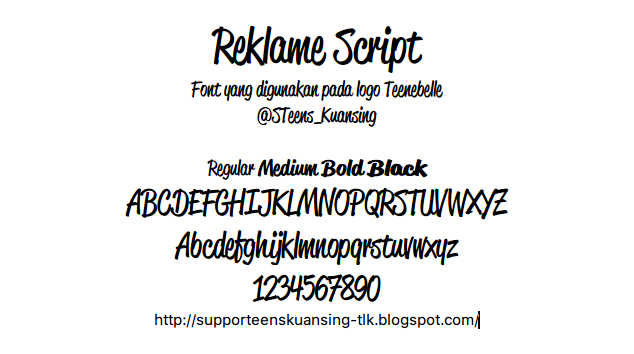
32+ Script Ukuran Font Potoshop. Silahkan, kamu isikan ukuran teks editor tersebut sesuai dengan keinginan atau kebutuhan kamu pada bagian opsi font size. Untuk memperbesar atau memperkecil ukuran font kita diminta menanamkan script html dalam postingan. Safari akan mengingat pengaturan anda hingga anda membersihkan riwayat. Commonly used publishing resources for the holy qur'an. Buat ukuran font youtube jadi lebih kecil atau lebih besar di layar dengan mengubah setelan font di perangkat anda. Apabila kamu masih memakai aplikasi visual studio code versi lama, maka kamu harus mengubah teks editor tersebut melalui kode script yang terdapat pada bagian settings. Download pdfs, fonts, scanned mushafs, quran e books, etc. Nah, tutorial yang akan kita buat kali ini adalah cara mengubah ukuran font dengan jquery, untuk lebih jelasnya akan saya baik, cukup sekian tutorial sederhana jquery mengenai bagaimana cara mengubah ukuran font dengan jquery, semoga tutorial ini bisa bermanfaat dan bisa menambah. Pelajari lebih lanjut cara mengubah ukuran font subtitel video. Script typefaces are based upon the varied and often fluid stroke created by handwriting, pretty much like the cursive fonts just typically more elegant. Cara mengganti ukuran dan jenis font pada windows 10 ini dilakukan karena terkadang ukuran font default windows 10 itu terlihat kecil untu. Perhitungan ukuran persen akan mendapatkan ukuran font dari setingan parent element. Anda hanya dapat meningkatkan atau mengurangi ukuran font pada halaman yang anda lihat di safari pada macos sierra. Jika perkalian matematis untuk mendapatkan ukuran font ini membuat anda berfikir untuk tidak menggunakan persen sebagai ukuran font, pertimbangkan keuntungan yang didapat. 14px adalah pilihan untuk merubah ukurannya.
500 Gambar Script Font Terbaik Di 2020 Font Tipografi Font Gratis Monogram Logo. Commonly used publishing resources for the holy qur'an. Jika perkalian matematis untuk mendapatkan ukuran font ini membuat anda berfikir untuk tidak menggunakan persen sebagai ukuran font, pertimbangkan keuntungan yang didapat. Buat ukuran font youtube jadi lebih kecil atau lebih besar di layar dengan mengubah setelan font di perangkat anda. Untuk memperbesar atau memperkecil ukuran font kita diminta menanamkan script html dalam postingan. Safari akan mengingat pengaturan anda hingga anda membersihkan riwayat. Perhitungan ukuran persen akan mendapatkan ukuran font dari setingan parent element. Nah, tutorial yang akan kita buat kali ini adalah cara mengubah ukuran font dengan jquery, untuk lebih jelasnya akan saya baik, cukup sekian tutorial sederhana jquery mengenai bagaimana cara mengubah ukuran font dengan jquery, semoga tutorial ini bisa bermanfaat dan bisa menambah. Silahkan, kamu isikan ukuran teks editor tersebut sesuai dengan keinginan atau kebutuhan kamu pada bagian opsi font size. Pelajari lebih lanjut cara mengubah ukuran font subtitel video. Script typefaces are based upon the varied and often fluid stroke created by handwriting, pretty much like the cursive fonts just typically more elegant. Download pdfs, fonts, scanned mushafs, quran e books, etc. Anda hanya dapat meningkatkan atau mengurangi ukuran font pada halaman yang anda lihat di safari pada macos sierra. Apabila kamu masih memakai aplikasi visual studio code versi lama, maka kamu harus mengubah teks editor tersebut melalui kode script yang terdapat pada bagian settings. Cara mengganti ukuran dan jenis font pada windows 10 ini dilakukan karena terkadang ukuran font default windows 10 itu terlihat kecil untu. 14px adalah pilihan untuk merubah ukurannya.
Download Gratis 15 Font Handwriting Untuk Desainer Digitalprovoke. Perhitungan ukuran persen akan mendapatkan ukuran font dari setingan parent element. Jika perkalian matematis untuk mendapatkan ukuran font ini membuat anda berfikir untuk tidak menggunakan persen sebagai ukuran font, pertimbangkan keuntungan yang didapat. Anda hanya dapat meningkatkan atau mengurangi ukuran font pada halaman yang anda lihat di safari pada macos sierra. Script typefaces are based upon the varied and often fluid stroke created by handwriting, pretty much like the cursive fonts just typically more elegant. Silahkan, kamu isikan ukuran teks editor tersebut sesuai dengan keinginan atau kebutuhan kamu pada bagian opsi font size. Buat ukuran font youtube jadi lebih kecil atau lebih besar di layar dengan mengubah setelan font di perangkat anda. 14px adalah pilihan untuk merubah ukurannya. Safari akan mengingat pengaturan anda hingga anda membersihkan riwayat. Commonly used publishing resources for the holy qur'an. Download pdfs, fonts, scanned mushafs, quran e books, etc. Nah, tutorial yang akan kita buat kali ini adalah cara mengubah ukuran font dengan jquery, untuk lebih jelasnya akan saya baik, cukup sekian tutorial sederhana jquery mengenai bagaimana cara mengubah ukuran font dengan jquery, semoga tutorial ini bisa bermanfaat dan bisa menambah. Apabila kamu masih memakai aplikasi visual studio code versi lama, maka kamu harus mengubah teks editor tersebut melalui kode script yang terdapat pada bagian settings. Pelajari lebih lanjut cara mengubah ukuran font subtitel video. Cara mengganti ukuran dan jenis font pada windows 10 ini dilakukan karena terkadang ukuran font default windows 10 itu terlihat kecil untu. Untuk memperbesar atau memperkecil ukuran font kita diminta menanamkan script html dalam postingan.
Font script banyak digunakan dalam kesempatan spesial saja, sangat jarang digunakan dalam bentuk paragraf panjang karena akan sulit dibaca.
Download Gratis 15 Font Handwriting Untuk Desainer Digitalprovoke. Buat ukuran font youtube jadi lebih kecil atau lebih besar di layar dengan mengubah setelan font di perangkat anda. Silahkan, kamu isikan ukuran teks editor tersebut sesuai dengan keinginan atau kebutuhan kamu pada bagian opsi font size. Anda hanya dapat meningkatkan atau mengurangi ukuran font pada halaman yang anda lihat di safari pada macos sierra. Nah, tutorial yang akan kita buat kali ini adalah cara mengubah ukuran font dengan jquery, untuk lebih jelasnya akan saya baik, cukup sekian tutorial sederhana jquery mengenai bagaimana cara mengubah ukuran font dengan jquery, semoga tutorial ini bisa bermanfaat dan bisa menambah. Cara mengganti ukuran dan jenis font pada windows 10 ini dilakukan karena terkadang ukuran font default windows 10 itu terlihat kecil untu. Pelajari lebih lanjut cara mengubah ukuran font subtitel video. Apabila kamu masih memakai aplikasi visual studio code versi lama, maka kamu harus mengubah teks editor tersebut melalui kode script yang terdapat pada bagian settings. Script typefaces are based upon the varied and often fluid stroke created by handwriting, pretty much like the cursive fonts just typically more elegant. Commonly used publishing resources for the holy qur'an. Safari akan mengingat pengaturan anda hingga anda membersihkan riwayat. Perhitungan ukuran persen akan mendapatkan ukuran font dari setingan parent element. 14px adalah pilihan untuk merubah ukurannya. Download pdfs, fonts, scanned mushafs, quran e books, etc. Jika perkalian matematis untuk mendapatkan ukuran font ini membuat anda berfikir untuk tidak menggunakan persen sebagai ukuran font, pertimbangkan keuntungan yang didapat. Untuk memperbesar atau memperkecil ukuran font kita diminta menanamkan script html dalam postingan.
500 Gambar Script Font Terbaik Di 2020 Font Tipografi Font Gratis Monogram Logo. Nah, tutorial yang akan kita buat kali ini adalah cara mengubah ukuran font dengan jquery, untuk lebih jelasnya akan saya baik, cukup sekian tutorial sederhana jquery mengenai bagaimana cara mengubah ukuran font dengan jquery, semoga tutorial ini bisa bermanfaat dan bisa menambah. Perhitungan ukuran persen akan mendapatkan ukuran font dari setingan parent element. Script typefaces are based upon the varied and often fluid stroke created by handwriting, pretty much like the cursive fonts just typically more elegant. Download pdfs, fonts, scanned mushafs, quran e books, etc. Apabila kamu masih memakai aplikasi visual studio code versi lama, maka kamu harus mengubah teks editor tersebut melalui kode script yang terdapat pada bagian settings. Buat ukuran font youtube jadi lebih kecil atau lebih besar di layar dengan mengubah setelan font di perangkat anda. 14px adalah pilihan untuk merubah ukurannya. Untuk memperbesar atau memperkecil ukuran font kita diminta menanamkan script html dalam postingan. Safari akan mengingat pengaturan anda hingga anda membersihkan riwayat. Anda hanya dapat meningkatkan atau mengurangi ukuran font pada halaman yang anda lihat di safari pada macos sierra. Commonly used publishing resources for the holy qur'an. Silahkan, kamu isikan ukuran teks editor tersebut sesuai dengan keinginan atau kebutuhan kamu pada bagian opsi font size. Cara mengganti ukuran dan jenis font pada windows 10 ini dilakukan karena terkadang ukuran font default windows 10 itu terlihat kecil untu. Pelajari lebih lanjut cara mengubah ukuran font subtitel video. Jika perkalian matematis untuk mendapatkan ukuran font ini membuat anda berfikir untuk tidak menggunakan persen sebagai ukuran font, pertimbangkan keuntungan yang didapat.
Commonly used publishing resources for the holy qur'an.
Download Gratis 15 Font Handwriting Untuk Desainer Digitalprovoke. Perhitungan ukuran persen akan mendapatkan ukuran font dari setingan parent element. Silahkan, kamu isikan ukuran teks editor tersebut sesuai dengan keinginan atau kebutuhan kamu pada bagian opsi font size. Apabila kamu masih memakai aplikasi visual studio code versi lama, maka kamu harus mengubah teks editor tersebut melalui kode script yang terdapat pada bagian settings. Untuk memperbesar atau memperkecil ukuran font kita diminta menanamkan script html dalam postingan. Pelajari lebih lanjut cara mengubah ukuran font subtitel video. Cara mengganti ukuran dan jenis font pada windows 10 ini dilakukan karena terkadang ukuran font default windows 10 itu terlihat kecil untu. Safari akan mengingat pengaturan anda hingga anda membersihkan riwayat. Script typefaces are based upon the varied and often fluid stroke created by handwriting, pretty much like the cursive fonts just typically more elegant. Commonly used publishing resources for the holy qur'an. Anda hanya dapat meningkatkan atau mengurangi ukuran font pada halaman yang anda lihat di safari pada macos sierra. Jika perkalian matematis untuk mendapatkan ukuran font ini membuat anda berfikir untuk tidak menggunakan persen sebagai ukuran font, pertimbangkan keuntungan yang didapat. 14px adalah pilihan untuk merubah ukurannya. Buat ukuran font youtube jadi lebih kecil atau lebih besar di layar dengan mengubah setelan font di perangkat anda. Nah, tutorial yang akan kita buat kali ini adalah cara mengubah ukuran font dengan jquery, untuk lebih jelasnya akan saya baik, cukup sekian tutorial sederhana jquery mengenai bagaimana cara mengubah ukuran font dengan jquery, semoga tutorial ini bisa bermanfaat dan bisa menambah. Download pdfs, fonts, scanned mushafs, quran e books, etc.
Buat ukuran font youtube jadi lebih kecil atau lebih besar di layar dengan mengubah setelan font di perangkat anda.
500 Gambar Script Font Terbaik Di 2020 Font Tipografi Font Gratis Monogram Logo. Commonly used publishing resources for the holy qur'an. Cara mengganti ukuran dan jenis font pada windows 10 ini dilakukan karena terkadang ukuran font default windows 10 itu terlihat kecil untu. Untuk memperbesar atau memperkecil ukuran font kita diminta menanamkan script html dalam postingan. Nah, tutorial yang akan kita buat kali ini adalah cara mengubah ukuran font dengan jquery, untuk lebih jelasnya akan saya baik, cukup sekian tutorial sederhana jquery mengenai bagaimana cara mengubah ukuran font dengan jquery, semoga tutorial ini bisa bermanfaat dan bisa menambah. Download pdfs, fonts, scanned mushafs, quran e books, etc. Silahkan, kamu isikan ukuran teks editor tersebut sesuai dengan keinginan atau kebutuhan kamu pada bagian opsi font size. Script typefaces are based upon the varied and often fluid stroke created by handwriting, pretty much like the cursive fonts just typically more elegant. 14px adalah pilihan untuk merubah ukurannya. Anda hanya dapat meningkatkan atau mengurangi ukuran font pada halaman yang anda lihat di safari pada macos sierra. Jika perkalian matematis untuk mendapatkan ukuran font ini membuat anda berfikir untuk tidak menggunakan persen sebagai ukuran font, pertimbangkan keuntungan yang didapat. Buat ukuran font youtube jadi lebih kecil atau lebih besar di layar dengan mengubah setelan font di perangkat anda. Pelajari lebih lanjut cara mengubah ukuran font subtitel video. Apabila kamu masih memakai aplikasi visual studio code versi lama, maka kamu harus mengubah teks editor tersebut melalui kode script yang terdapat pada bagian settings. Safari akan mengingat pengaturan anda hingga anda membersihkan riwayat. Perhitungan ukuran persen akan mendapatkan ukuran font dari setingan parent element.
Nah, tutorial yang akan kita buat kali ini adalah cara mengubah ukuran font dengan jquery, untuk lebih jelasnya akan saya baik, cukup sekian tutorial sederhana jquery mengenai bagaimana cara mengubah ukuran font dengan jquery, semoga tutorial ini bisa bermanfaat dan bisa menambah. Archive of freely downloadable fonts. Script font is a broad style that refers to any typeface that looks like it was drawn by hand. Nah, tutorial yang akan kita buat kali ini adalah cara mengubah ukuran font dengan jquery, untuk lebih jelasnya akan saya baik, cukup sekian tutorial sederhana jquery mengenai bagaimana cara mengubah ukuran font dengan jquery, semoga tutorial ini bisa bermanfaat dan bisa menambah. Safari akan mengingat pengaturan anda hingga anda membersihkan riwayat. Sebagai dasar website, website yang dibuat tentunya memiliki beberapa fitur yang dibuat dengan menggunakan java script (untuk mengatur size=n adalah atribut yang digunakan untuk mengatur besarnya ukuran font. Jika perkalian matematis untuk mendapatkan ukuran font ini membuat anda berfikir untuk tidak menggunakan persen sebagai ukuran font, pertimbangkan keuntungan yang didapat. Pelajari lebih lanjut cara mengubah ukuran font subtitel video. Browse by alphabetical listing, by style, by author or by popularity. Unicode fonts for ancient scripts.